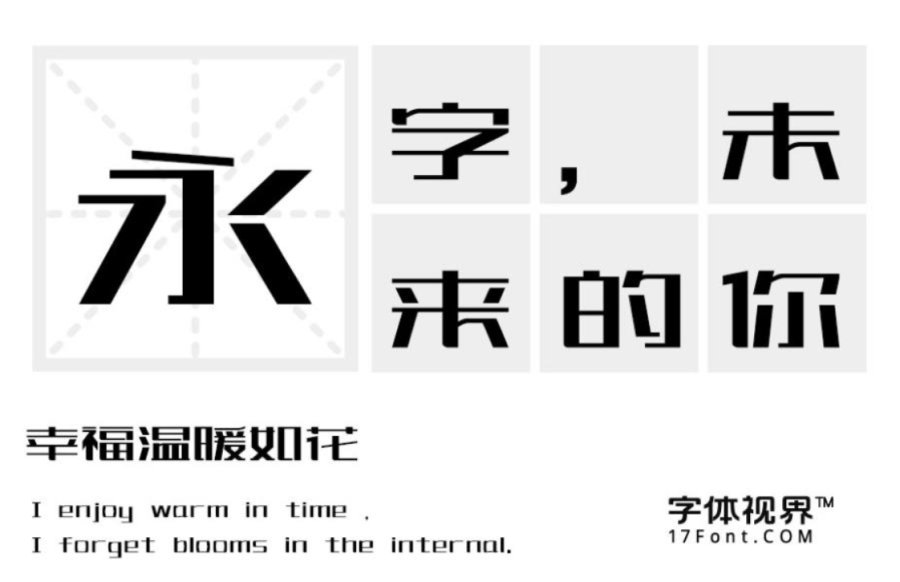
上首宽窄体|一款张弛有度的创意字体
上首宽窄体发布
字体名称:上首宽窄体
字体类别:创意字体
上首宽窄体简介:上首宽窄体,字体风格稳重呈方块形,粗壮的竖笔画给人一种稳重感,搭配细小的横笔画,二者相结合,产生一种协调美,是此套字库的亮点。字库整体特征有力、又参杂着柔和,具有现代、国际化的指向性,适用于搭配标志、广告标语、商业广告等高端属性。
上首宽窄体预览图展示: